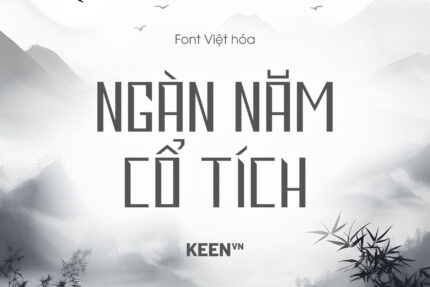
Font Việt hóa OAI Ironfist
Font Việt hóa OAI Ironfist mang dáng vẻ mạnh mẽ và dứt khoát với cấu trúc chữ cao, hẹp và thiên về hình khối thẳng đứng. Các nét chữ được thiết kế dày, gọn và gần như không có độ uốn cong, tạo nên cảm giác chắc chắn và có phần kỷ luật, giống như những ký tự được cắt từ các thanh kim loại hoặc dựng lên từ những khối kiến trúc. Điểm đáng chú ý của kiểu chữ này nằm ở các góc cắt vát và chi tiết đầu nét được xử lý gãy gọn, giúp từng ký tự có cá tính rõ rệt nhưng vẫn giữ được sự đồng bộ trong tổng thể. Khi hiển thị tiếng Việt, các dấu được đặt theo cùng logic hình học của thân chữ, tạo cảm giác liền mạch và không phá vỡ nhịp điệu thẳng đứng đặc trưng.
Nhờ phong thái cứng cáp và hiện đại, Font Việt hóa OAI Ironfist thường phù hợp cho các thiết kế tiêu đề mang tính mạnh mẽ như poster sự kiện, banner thể thao, thiết kế game, bìa album hoặc các dự án nhận diện thương hiệu cần truyền tải cảm giác năng lượng, sức mạnh và sự dứt khoát trong thị giác.